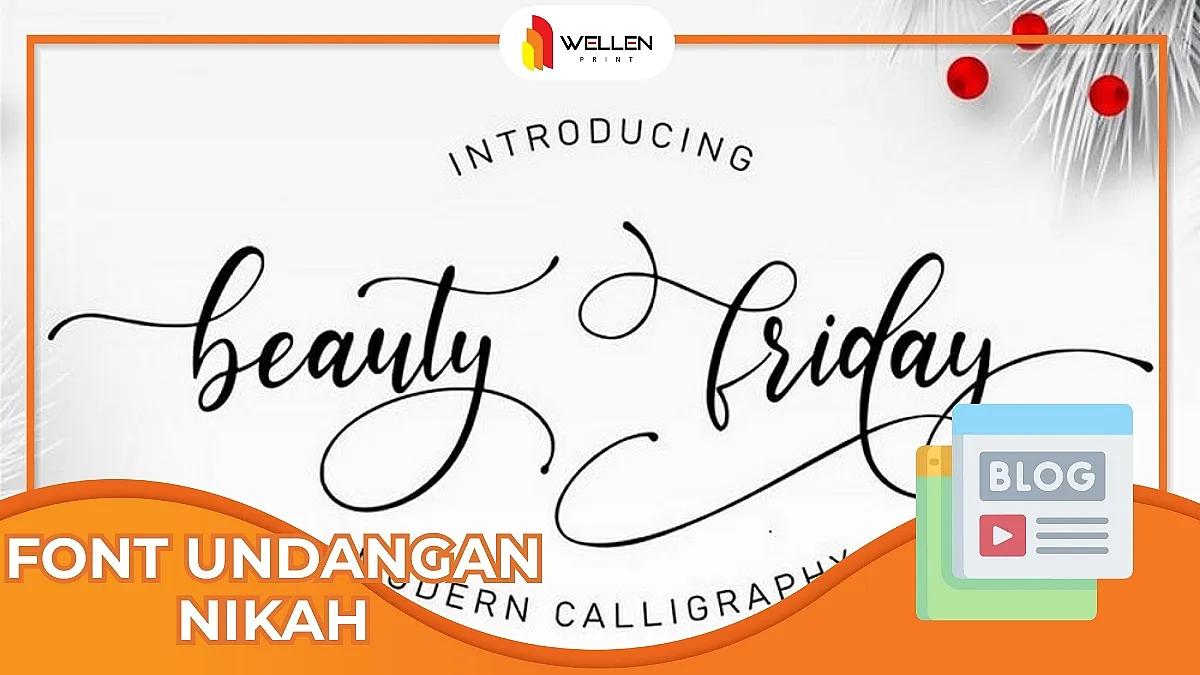
10 Jenis Font Terbaik untuk Undangan Pernikahan
Undangan pernikahan harus terlihat elegan, estetik, dan detail untuk menunjukkan keseriusan dalam mengharapkan kehadiran tamu. Salah satu elemen kunci yang berpengaruh besar dalam hal tersebut adalah font atau tipografi yang digunakan. pemilihan font untuk undangan pernikahan yang tepat dapat meningkatkan estetika dan keterbacaan informasinya.
Secara teknis, ada tiga jenis kelompok tipografi yang cocok menjadi pilihan sebagai font undangan pernikahan, yaitu: Script yang elegan, Serif dengan citra klasik dan formal, serta Sans-Serif dengan tampilan modern minimalisnya. Supaya lebih mudah memilih, berikut 10 rekomendasi font aesthetic untuk undangan pernikahan dari tiga kelompok tipografi tersebut.
Font Script adalah kelompok tipografi yang terinspirasi dari gaya tulisan tangan asli manusia. Karakteristik berbagai font dalam kelompok ini melengkung dan mengalir sehingga menciptakan kesan romantis, personal, dan eksklusif. Ada 5 macam font Script populer untuk diaplikasikan pada undangan pernikahan, yaitu: Great Vibes, Allura, Alex Brush, Dancing Script, dan Pacifico.
Font Great Vibes dirancang oleh Rob Leuschke, seorang desainer tipografi dengan spesialisasi kaligrafi dan Script, sekaligus pemilik studio TypeSETit. Setiap huruf pada Great Vibes dirancang untuk menyambung dengan huruf berikutnya secara mulus, menyerupai tulisan tangan halus menggunakan pena celup atau kuas kecil. Cocok untuk menuliskan nama mempelai pada undangan pernikahan.
Allura adalah font undangan pernikahan free yang juga diciptakan desainer Great Vibes. Jenis tipografi satu ini menawarkan gaya yang lebih modern, menggabungkan citra kasual dan formal dengan komposisi pas. Sambungan hurufnya mirip penulisan dengan pena tanpa putus dan memiliki ketebalan standar. Cocok untuk menulis kutipan pernikahan atau nama penerima undangan.
Masih diciptakan oleh desainer tipografi yang sama dengan dua contoh sebelumnya, Alex Brush juga cocok sebagai font untuk undangan pernikahan. Font ini memiliki batang huruf pendek yang membuat tulisan jadi lebih terorganisir. Keunggulan utamanya adalah tingkat keterbacaan paling tinggi di kelompok Script. Cocok untuk menuliskan calon pengantin atau penerima undangan.
Rekomendasi font untuk undangan pernikahan gratis selanjutnya adalah Dancing Script. Font ini diciptakan oleh Pablo Impallari dengan ciri khas huruf-huruf yang tidak sejajar pada satu garis tegak lurus sehingga menciptakan efek menyerupai gerakan menari (dancing). Cocok untuk menuliskan informasi pada undangan pernikahan bertema outdoor atau garden party berkonsep semi formal.
Pacifico adalah font yang diciptakan oleh desainer tipografi asal Inggris, Vernon Adams. Inspirasinya dari poster-poster promosi pantai dan papan selancar yang menggunakan gaya tulisan tangan kuas (brush script). Garis huruf tebal, jadi cocok untuk menuliskan informasi singkat pada undangan seperti nama pengantin, penerima undangan, atau tanggal penyelenggaraan agar mudah terbaca.
Font Serif merupakan kelompok tipografi tertua. Sebab itu, jenis tipografi di dalamnya cenderung memiliki citra klasik dan formal yang kuat. Karakteristik utamanya adalah kait kecil di setiap akhir huruf yang membuatnya tidak lekang oleh zaman. Dua jenis font Serif yang paling direkomendasikan untuk undangan pernikahan adalah Garamond dan Playfair Display.
Garamond merupakan font yang terinspirasi karya pembuat cetakan huruf asal Paris: Claude Garamond, dan menjadi salah satu jenis tipografi paling legendaris di dunia. Masing-masing huruf memiliki transisi yang halus dengan tingkat keterbacaan sangat baik, sehingga cocok untuk penulisan informasi yang cukup panjang pada undangan pernikahan, seperti tanggal dan lokasi pesta.
Berikutnya ada Playfair Display yang menawarkan ukuran font untuk undangan pernikahan paling ideal. Desainer tipografi asal Denmark, Claus Eggers Sørensen, merupakan pencipta font dengan kontras tajam antara garis tebal dan tipis ini. Cocok untuk menuliskan informasi panjang pada undangan seperti detail penyelenggaraan serta memberikan kesan modern sekaligus mewah secara bersamaan.
Font Sans-Serif merupakan kelompok tipografi termuda dan merupakan versi modernisasi dari Serif. Secara teknis, diciptakan sebagai model penulisan minimalis yang futuristik dan sangat mudah terbaca. Ciri khasnya ada pada ketebalan huruf yang seragam. Ada tiga jenis font Sans-Serif yang cocok untuk diaplikasikan pada undangan pernikahan: Helvetica, Montserrat, dan Lato.
Helvetica merupakan font yang cocok untuk berbagai ukuran kertas undangan pernikahan. Penciptanya adalah Max Miedinger dan Eduard Hoffmann asal Swiss. Ciri khas font ini adalah tinggi huruf kecil tidak berbeda jauh dengan huruf kapital dan memiliki jarak pemisah (spasi) lebar yang membuat keterbacaannya sangat baik. Cocok untuk penulisan informasi panjang.
Montserrat diciptakan oleh Julieta Ulanovsky yang terinspirasi dari tulisan jalanan di Buenos Aires. Mudah dikenali dari bentuk geometris yang memiliki presisi tinggi, terutama pada lingkaran dan garis lurus yang tegas. Tingkat keterbacaan yang baik, bahkan dalam size terkecil, membuatnya cocok sebagai font ukuran label undangan berisi nama dan alamat penerima.